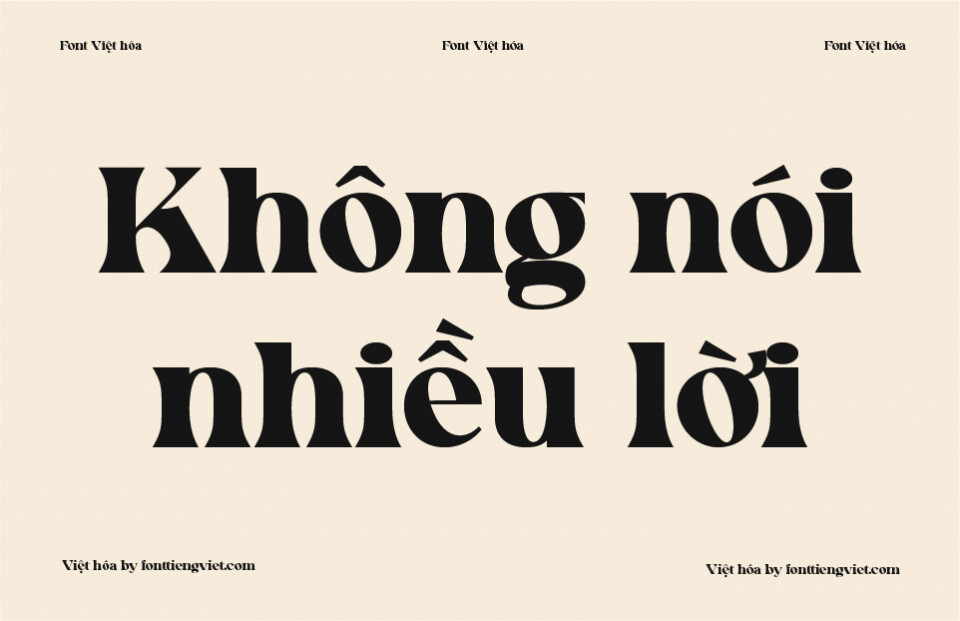
Font Việt hóa 1FTV VIP Swoxemun
Giới thiệu về bộ Font Việt hóa 1FTV VIP Swoxemun chuyên nghiệp
Trong thế giới thiết kế đồ họa hiện đại, việc lựa chọn một bộ phông chữ phù hợp đóng vai trò quyết định đến sự thành công của một sản phẩm truyền thông. Font Việt hóa 1FTV VIP Swoxemun là một trong những bộ phông chữ độc đáo, mang phong cách hiện đại và đầy cá tính, vừa được tối ưu hóa hoàn toàn cho người dùng tại Việt Nam. Khi tìm kiếm một Font Miễn Phí chất lượng cao, các nhà thiết kế thường ưu tiên những bộ font có khả năng hiển thị tiếng Việt mượt mà, không bị lỗi dấu, và 1FTV VIP Swoxemun chính là câu trả lời hoàn hảo. Bộ font này không chỉ sở hữu các đường nét tinh tế, sắc sảo mà còn giữ được sự cân đối trong từng con chữ, giúp nội dung của bạn trở nên nổi bật và thu hút thị giác ngay từ cái nhìn đầu tiên. Đối với các bạn học sinh và sinh viên, đây là công cụ hỗ trợ đắc lực để làm nổi bật các bài thuyết trình hoặc dự án cá nhân một cách chuyên nghiệp nhất.
Đặc điểm nổi bật của Font Việt hóa 1FTV VIP Swoxemun trong thiết kế
Phong cách thiết kế đột phá và linh hoạt
Font Việt hóa 1FTV VIP Swoxemun nổi bật với cấu trúc các chữ cái được thiết kế theo lối kiến trúc hiện đại, kết hợp giữa những đường thẳng mạnh mẽ và các góc bo tròn mềm mại. Điều này tạo nên một tổng thể hài hòa, phù hợp cho nhiều mục đích sử dụng khác nhau như thiết kế logo, làm tiêu đề poster, hay dàn trang tạp chí. Sự linh hoạt của bộ font này cho phép nó thích ứng tốt trên cả nền tảng in ấn truyền thống lẫn hiển thị kỹ thuật số. Đặc biệt, các ký tự tiếng Việt đã được tinh chỉnh kỹ lưỡng về khoảng cách và kích thước dấu, đảm bảo văn bản luôn dễ đọc và có tính thẩm mỹ cao nhất. Việc sử dụng 1FTV VIP Swoxemun sẽ giúp bản thiết kế của bạn thoát khỏi sự đơn điệu của những phông chữ hệ thống thông thường, mang lại một làn gió mới đầy sáng tạo và chuyên nghiệp.
Không chỉ dành riêng cho các designer chuyên nghiệp, Font Việt hóa 1FTV VIP Swoxemun còn rất thân thiện với môi trường học đường. Các em học sinh có thể sử dụng font chữ này để thiết kế bìa báo tường, làm slide bài giảng điện tử hoặc tạo ra các thiệp chúc mừng ý nghĩa. Sự rõ ràng trong nét chữ giúp người xem dễ dàng tiếp nhận thông tin mà không gây mỏi mắt. Bên cạnh đó, các giáo viên cũng có thể ứng dụng font này vào việc soạn thảo tài liệu giảng dạy sinh động hơn, giúp khơi gợi hứng thú học tập cho học sinh. Với định dạng file chuẩn, bộ font dễ dàng cài đặt trên cả hệ điều hành Windows và macOS, tương thích tốt với các phần mềm phổ biến như Microsoft Word, PowerPoint, Photoshop hay Illustrator.
Kết luận về giá trị của bộ Font Việt hóa 1FTV VIP Swoxemun
Việc sở hữu một bộ font đẹp và chuẩn Việt hóa sẽ mở ra không gian sáng tạo vô tận cho mọi người. Font Việt hóa 1FTV VIP Swoxemun thực sự là một lựa chọn tuyệt vời cho bất kỳ ai đang tìm kiếm sự khác biệt và đẳng cấp trong ngôn ngữ thị giác. Với sự hỗ trợ đầy đủ về bảng mã và dấu tiếng Việt, bộ font này xứng đáng có mặt trong bộ sưu tập tài nguyên thiết kế của bạn. Hãy trải nghiệm ngay sức mạnh của ngôn từ thông qua những đường nét tinh tế của 1FTV VIP Swoxemun để nâng tầm giá trị cho mọi dự án. Đừng quên ghé thăm trang web Font Miễn Phí, Font Việt Hóa, Font Việt hóa 1FTV VIP Swoxemun thường xuyên để cập nhật thêm nhiều bộ phông chữ ấn tượng và hoàn toàn miễn phí khác dành riêng cho cộng đồng Việt Nam.